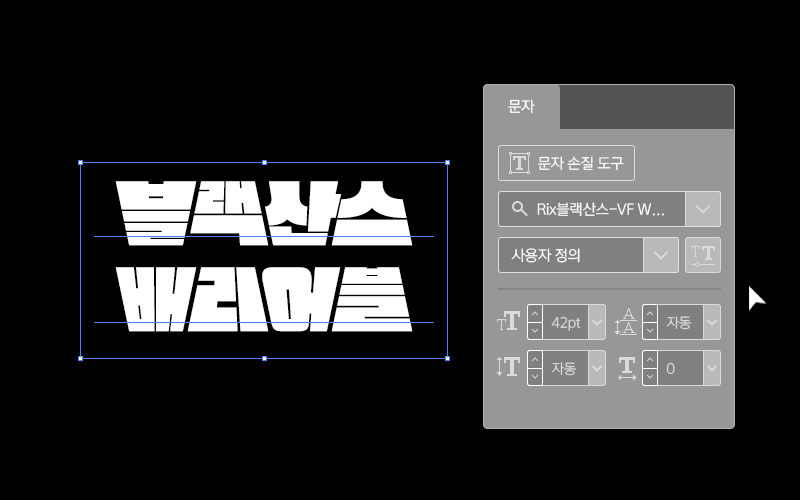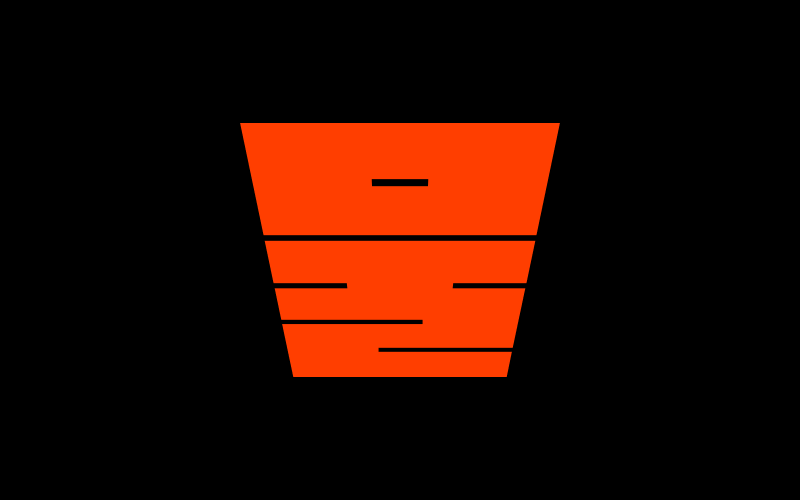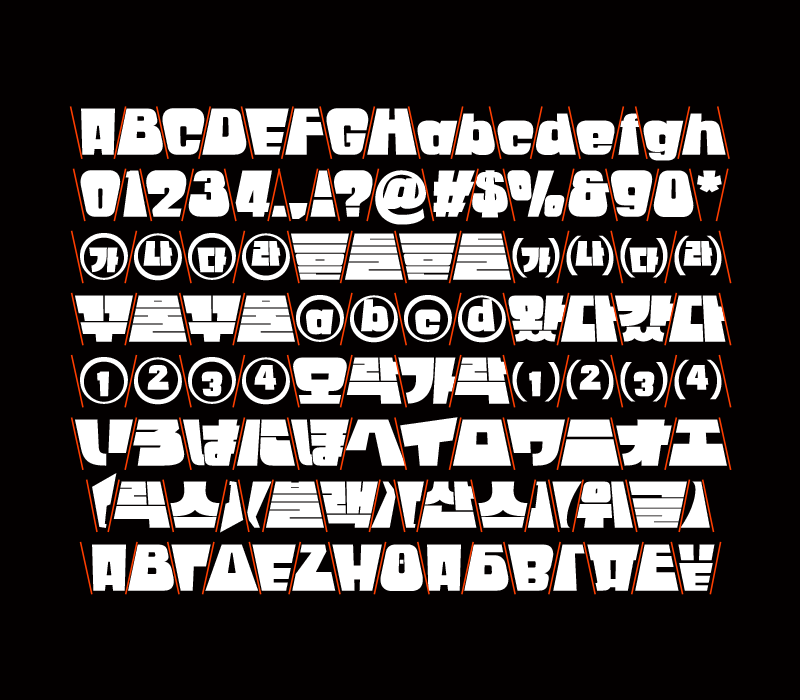
Rix블랙산스VF - Wiggle
RixBlackSans-VF-Wiggle
네모틀 꽉 찬 두꺼운 제목용 서체 Rix블랙산스를 기반으로 제작한 배리어블 폰트입니다.
사다리꼴의 글자 상하 폭이 번갈아가며 바뀌는 변형을 통해 위트 있고 강렬한 인상을 줍니다.
단단하고 개성 있는 형태가 시선을 사로잡아 주목도가 필요한 콘텐츠에 활용하기 좋습니다.
배리어블 폰트란, 사용자가 직접 글자의 속성을 조정할 수 있는 서체입니다.
사다리꼴 형태의 고정폭 한글 모듈을 사용합니다.
역방향 사다리꼴 모듈이 번갈아가며 타이핑됩니다.
영문과 숫자 및 약물에도 같은 효과를 적용해 국문과 혼용 시 자연스럽게 어울리도록 했습니다.